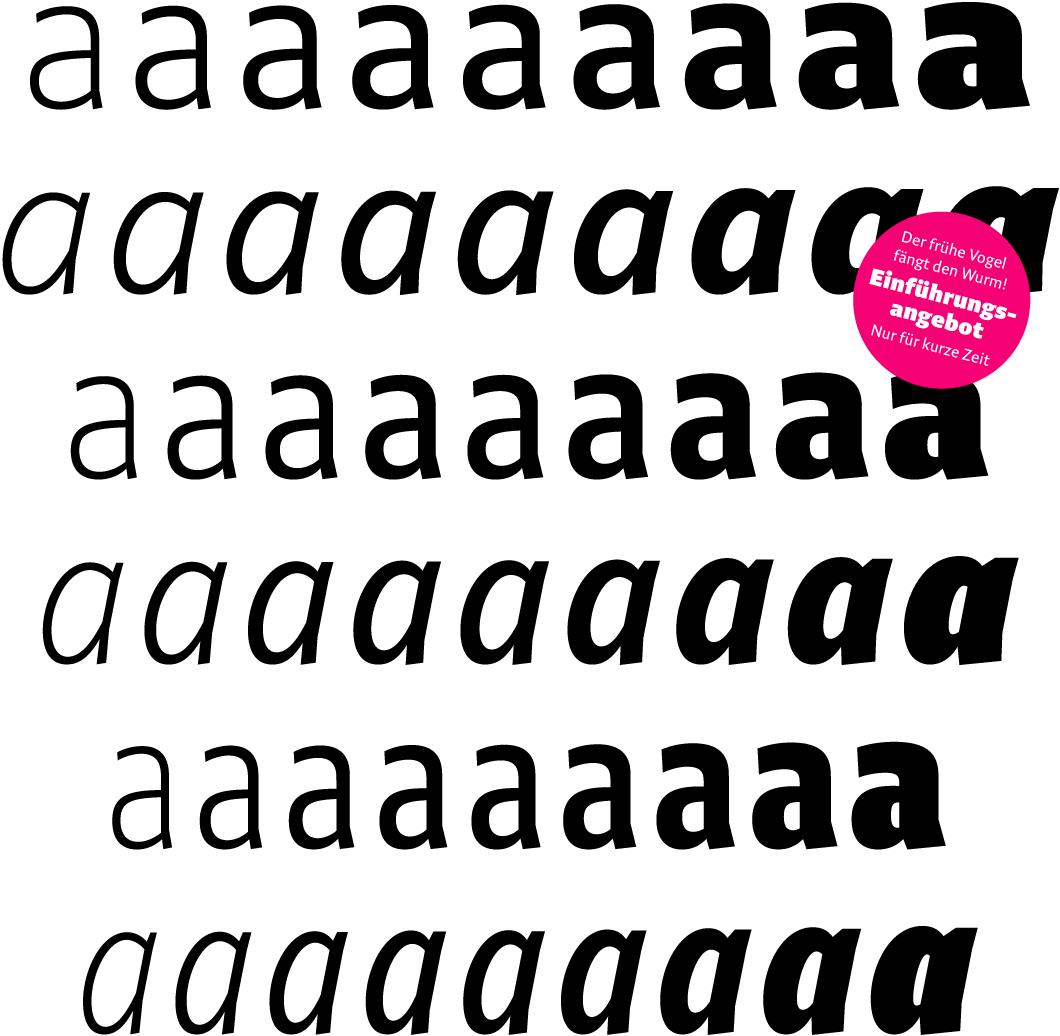
Für mich muss eine gute Schrift vor allem Lebendigkeit ausstrahlen. Um das zu erreichen, versuche ich unterschiedliche Charakterzüge in einer Schrift zu vereinen: Offenheit, Wärme und Freundlichkeit einerseits, Klarheit und Selbstbewusstsein andererseits. Niko zählt zu den humanistischen Serifenlosen, mit offenen Buchstabenformen, die sehr schön miteinander agieren, und beim Lesen das Auge entlang der Zeile führen. Das macht sie zu einer sehr guten Leseschrift. Markante Formen und eine gewisse Kantigkeit unterstützen nicht nur die Lesbarkeit, sondern macht sie auch in großen Schriftgrößen zu einem echten Blickfang.
Niko ist freundlich, aber nie Langweilig. In Textgrößen ist sie angenehm lesbar, in groß prägnant und ansprechend. Eine Schrift, wie sie im Buche steht. Und zu allem Überfluss: Sie ist auch noch unglaublich gut ausgebaut.
Mit 54 unterschiedlichen Schriftschnitten bietet Niko eine große typografische Flexibilität für alle nur denkbaren Anwendungen: Bücher, Magazine, Flyer, Poster, Corporate Design bis hin zu Webseiten und Apps. (Niko ist natürlich auch bildschirmoptimiert.) Und wenn es einmal eng wird, sind schmale und extra schmale Schriftschnitte ihr Freund.
Niko wurde ursprünglich als eine Schrift für Zeitungen entworfen, wo sie mit schlechten Druckbedingungen und typografischen Herausforderungen wie schmalen Spalten und sehr kleinen Schriftgrößen zurecht kommen musste. Inzwischen hat sie sich zu einer sehr vielfältig einsetzbaren Schriftfamilie entwickelt, die eigentlich immer ein gutes Bild abgibt.